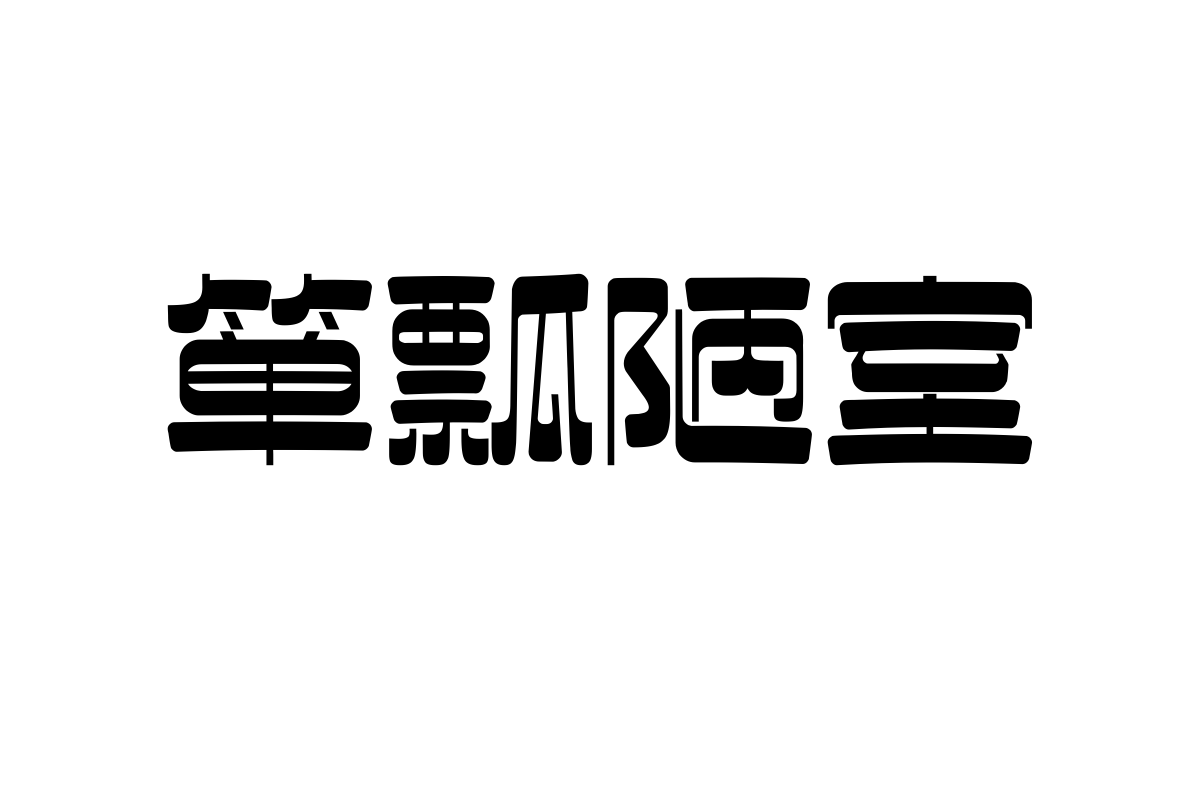
上首折扇体是一种中文字体。这种字体的特点是笔画流畅,字形优美,适合用于书法、绘画等艺术创作。它的特点是笔画圆润,结构紧凑,给人一种优雅、庄重的感觉。
上首折扇体的笔画粗细变化较大,既有细如发丝的细小笔触,也有粗如椽木的粗壮笔触。这种变化使得整个字体既有力度感,又不失柔和感,非常适合表现诗词中的意境和情感。
此外,上首折扇体的字形结构也非常独特。它的每个字都有独立的结构,但又相互关联,形成了一种独特的美感。这种美感使得上首折扇体在视觉上具有很强的冲击力和辨识度。
总的来说,上首折扇体是一种非常具有艺术感和个性的中文字体,非常适合用于需要表现艺术性和个性的场合。